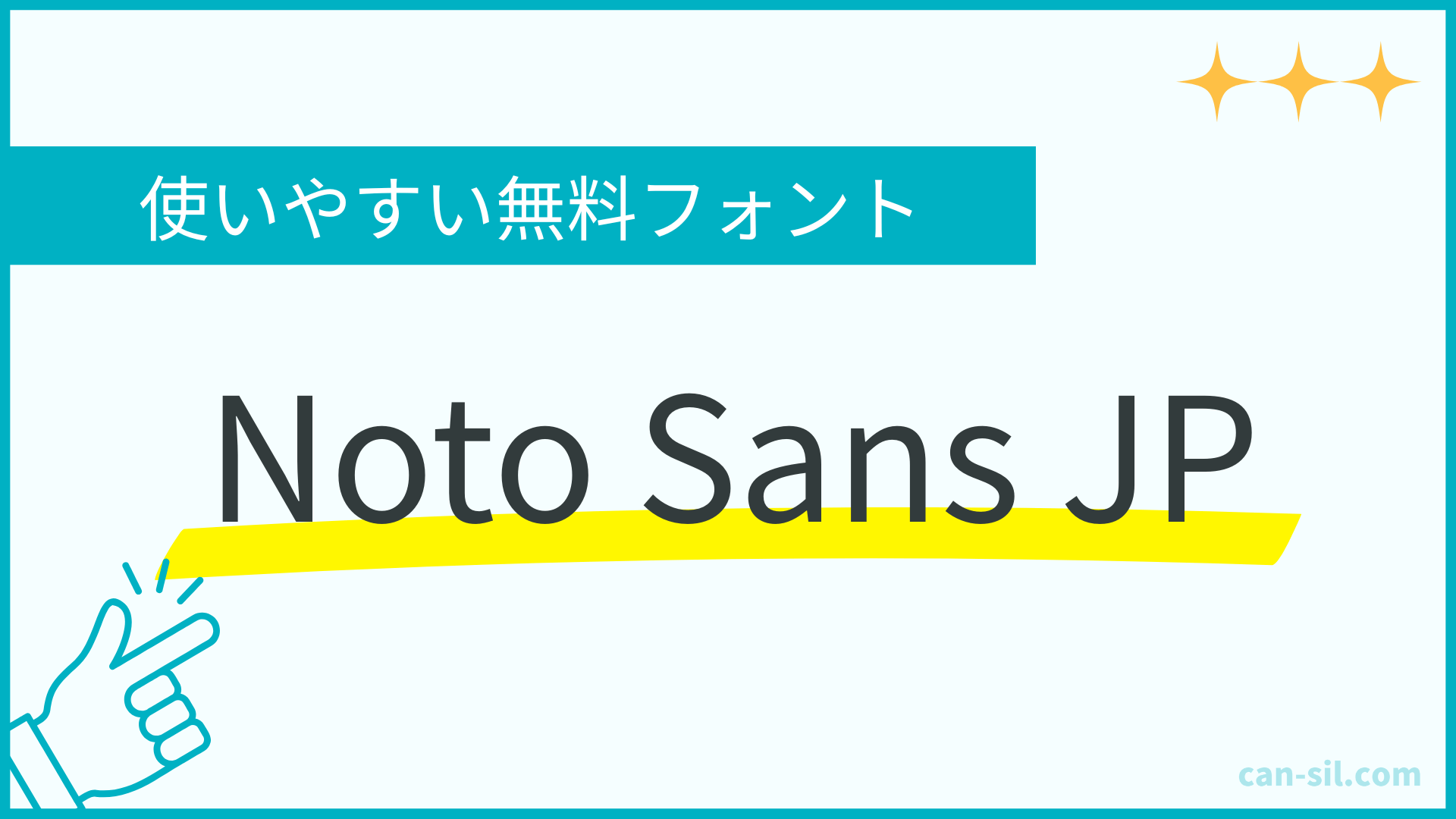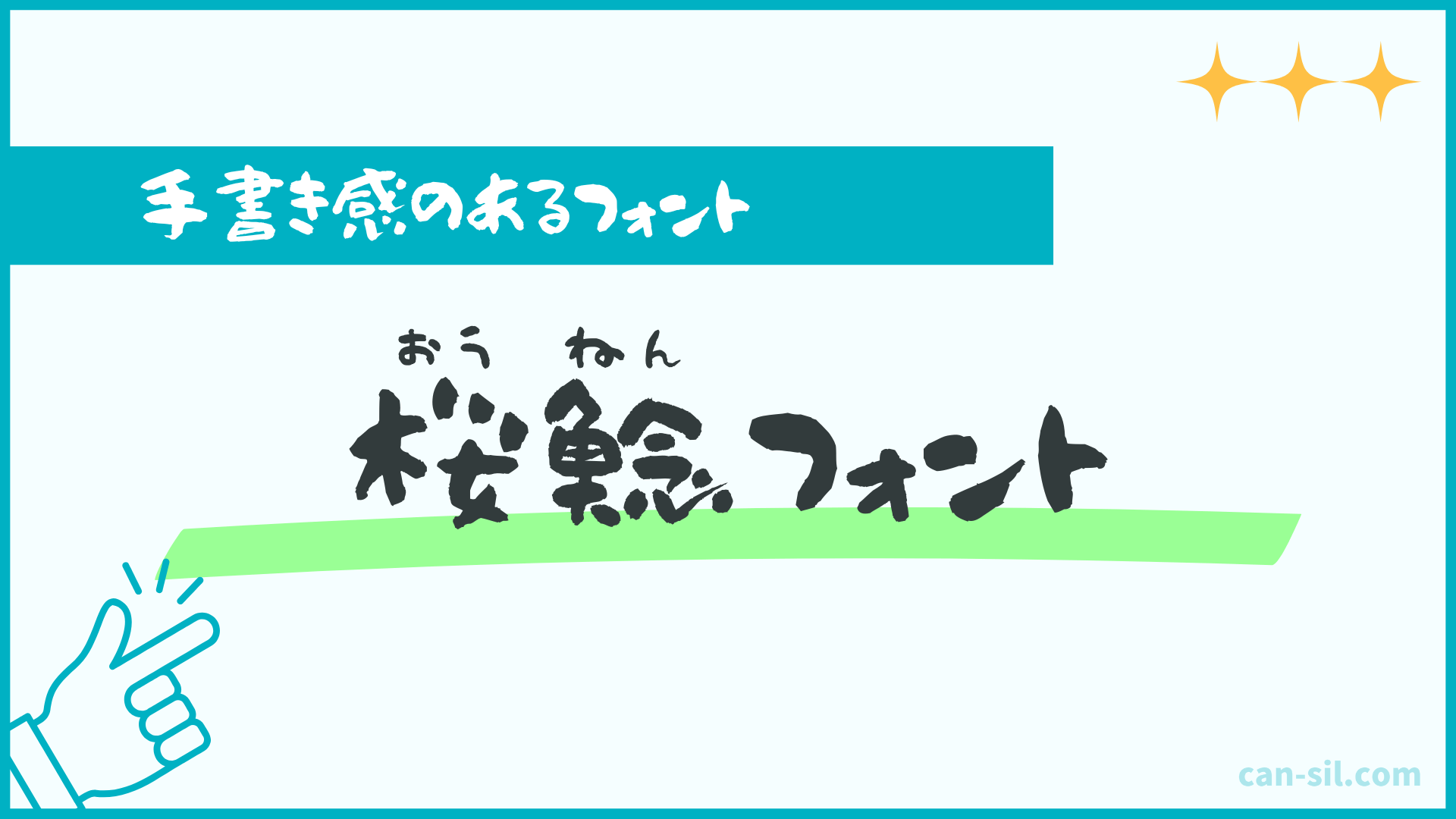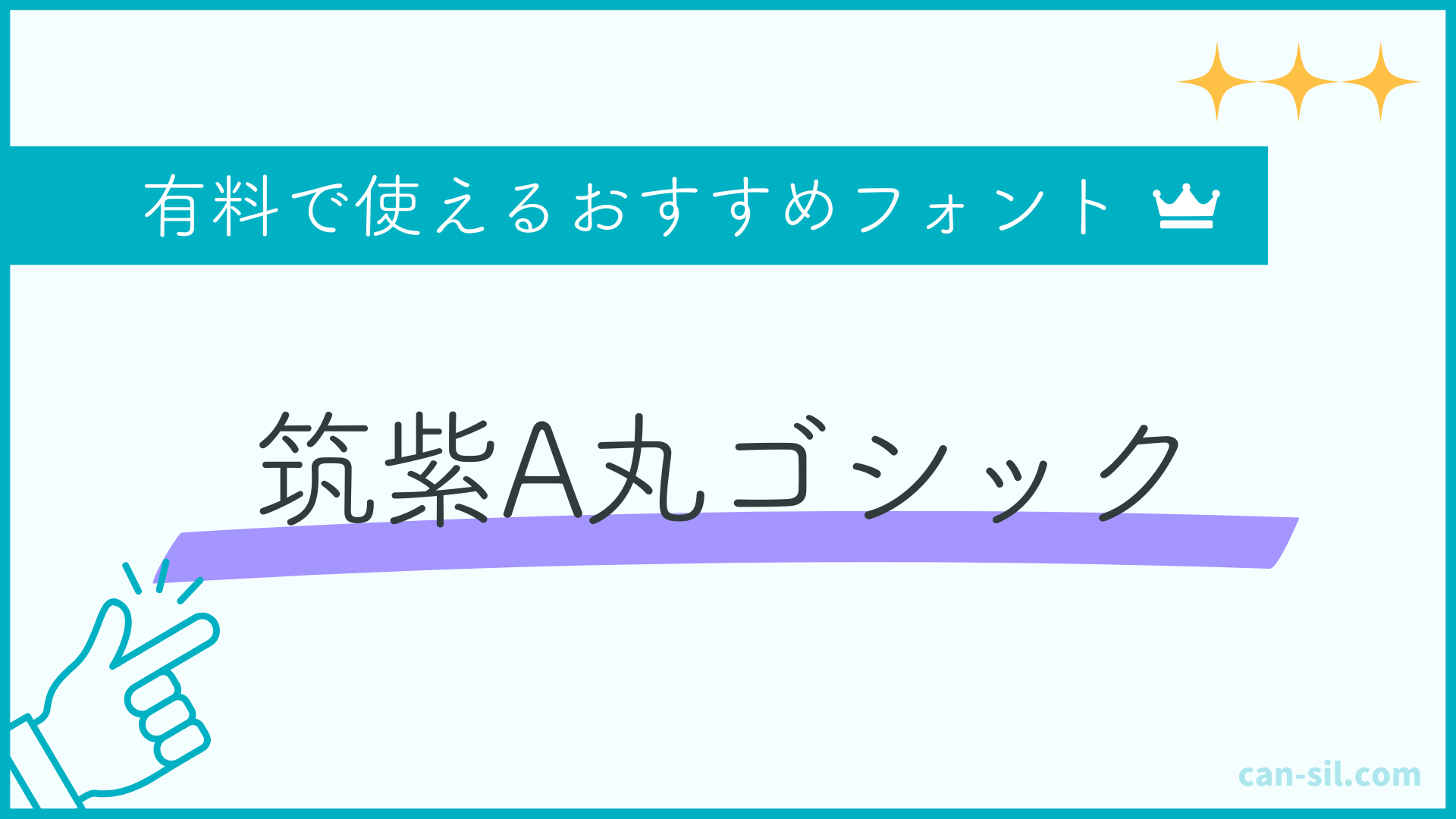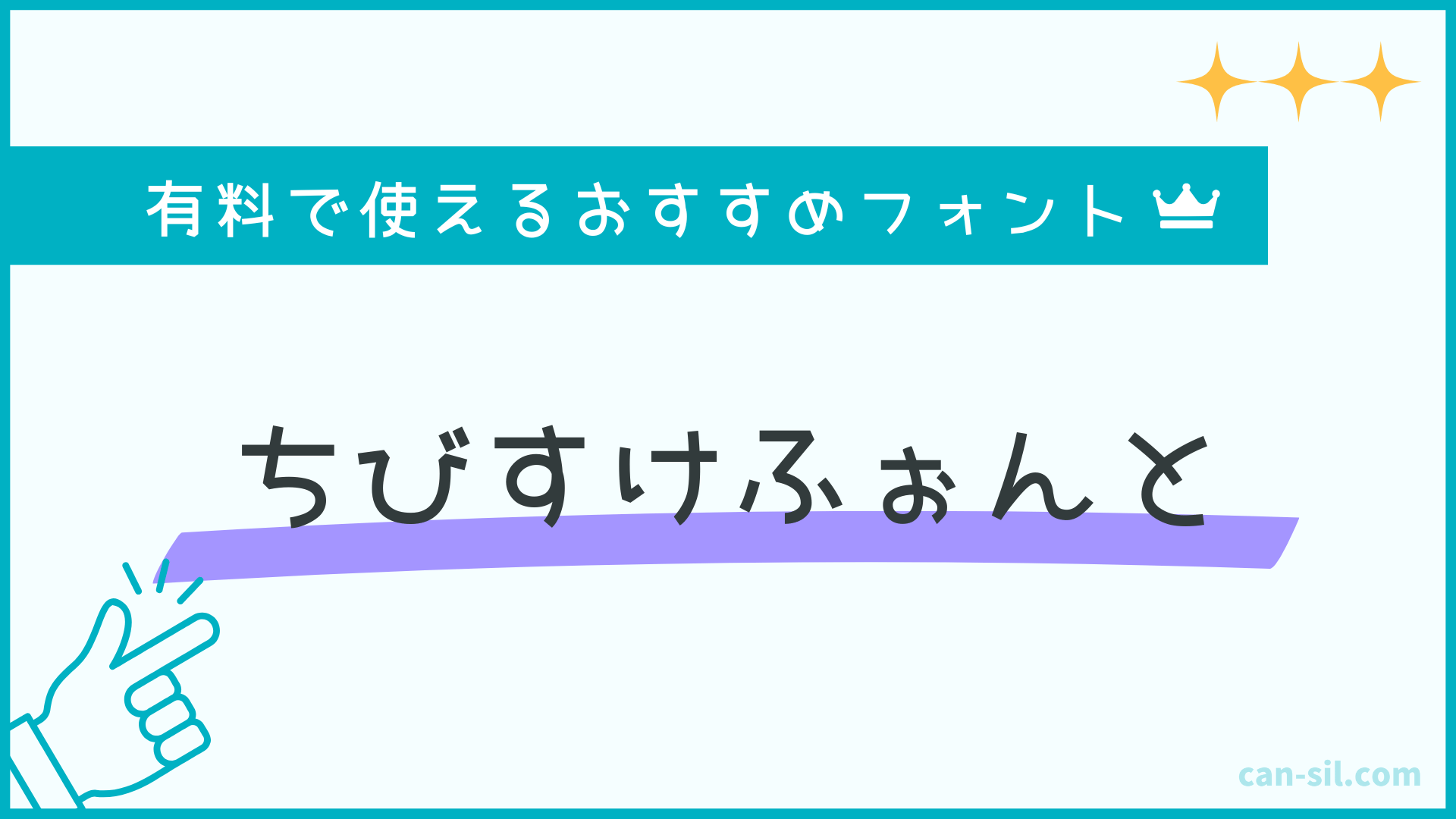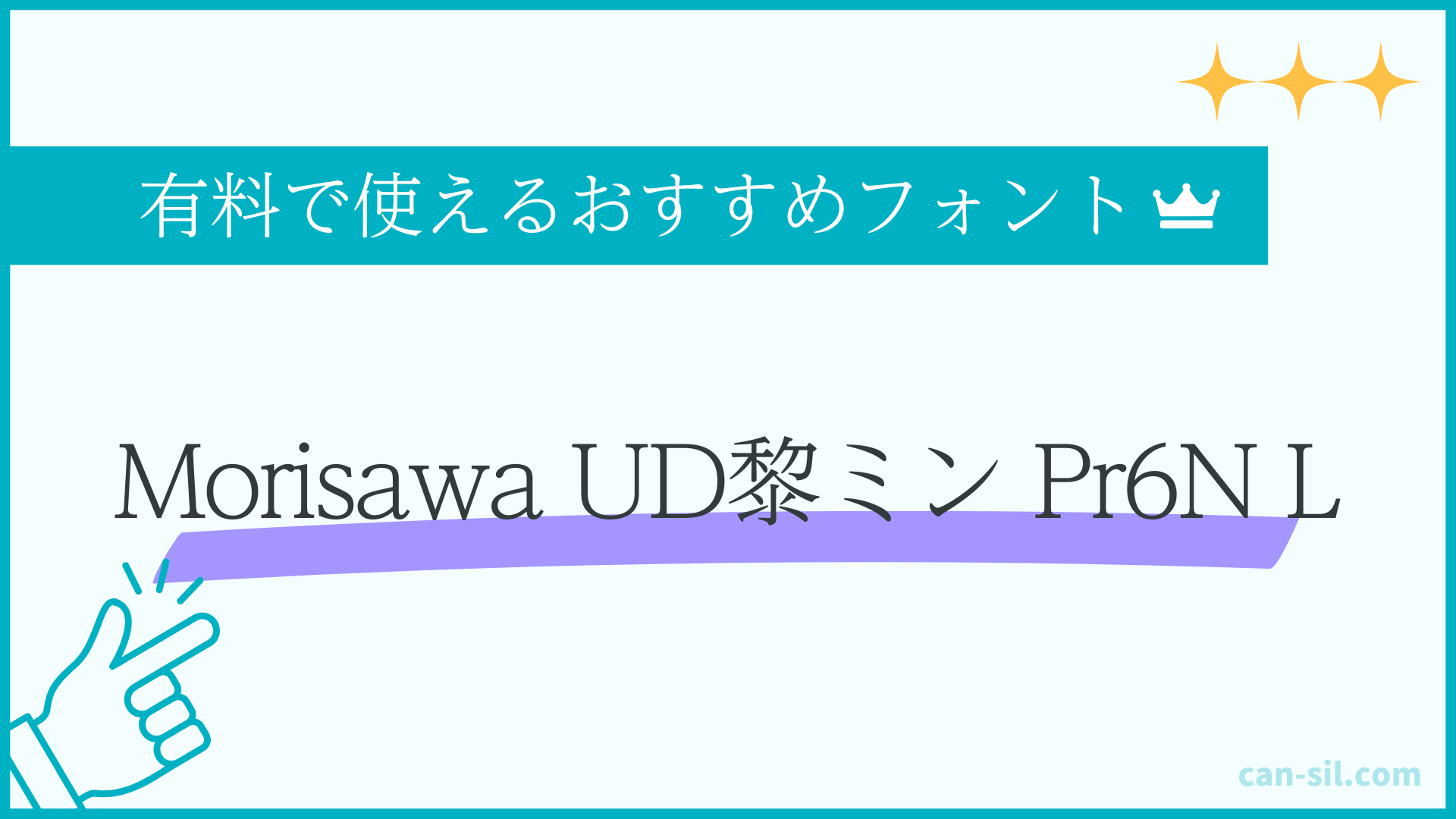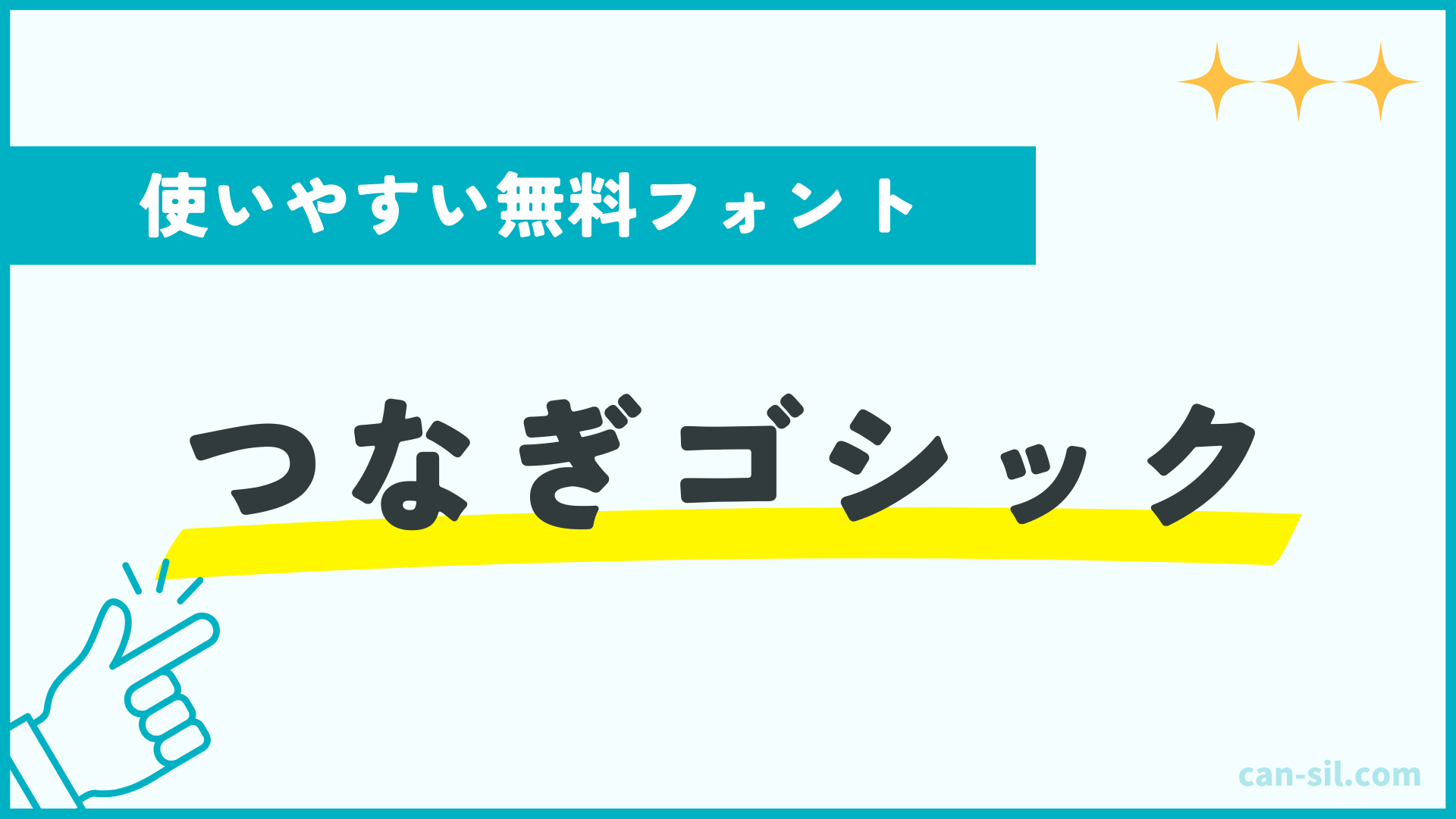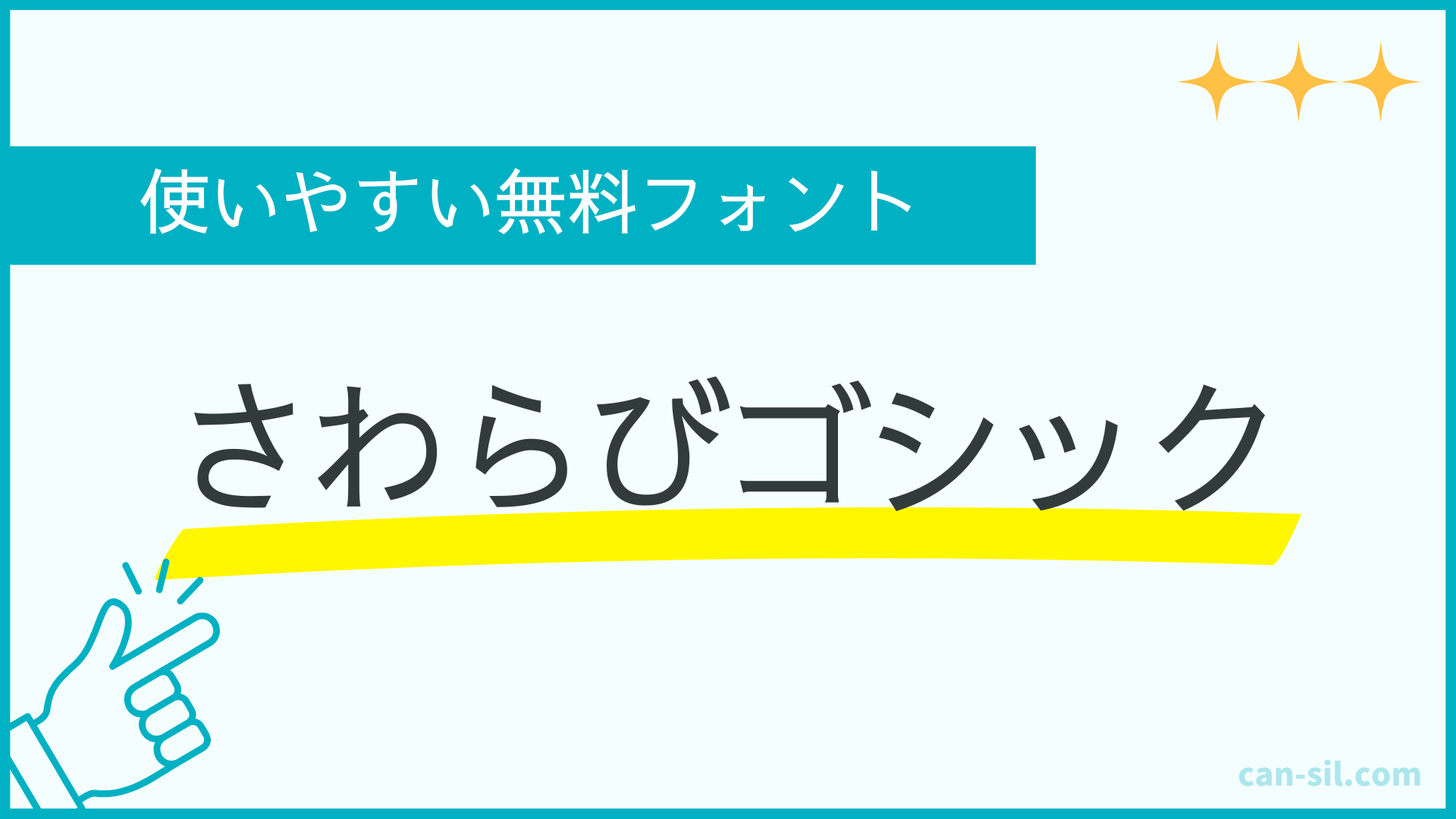
Canvaのおすすめフォント12選!アップロード方法や便利機能などもあわせて解説
Canvaフォントおすすめ12選とアップロード方法と便利機能
• 使いやすいおすすめのフォントはどれ?
• Canvaのフォントを使いこなすコツを教えてほしい!
Canvaでフォントを決めるとき、「もっと簡単に選びたい。」「使いたいこなしたい。」と考えていませんか?
この記事では、Canvaエキスパートのぼくがおすすめするフォントをいくつか紹介します!
おすすめフォント12選
おすすめフォント一覧
また、Canvaのフォントアップロードの方法や、より使いこなしたい人におすすめの便利機能についても、詳しく解説します。
ぜひ参考にして、明日からCanvaをもっと使いこなして、理想のデザインを実現しましょう。
Canvaでおすすめの日本語フォント12選を紹介!
Canvaおすすめフォント12選
無料で使いやすいフォント
まず最初に、無料で使える&どんなデザインにも使いやすいフォントを4つ紹介します。
ゴシック体と明朝体の2種類を紹介します。
Noto Sans JP
使いやすい無料フォント1「Noto Sans JP」
ゴシック体の中でもシンプルで使いやすいフォントです。
GoogleとAdobeにより共同開発されたフォントで、多くの言語に対応しているのが特徴です。
多くのデザインに使われている定番フォントです!
太さは6種類(極細、細め、標準、中太、太字、極太)から選べます。
つなぎゴシック
使いやすい無料フォント2「つなぎゴシック」
「Zen角ゴシックN」というフォントの角の丸を加工し、墨だまり処理をしたフォントです。太文字で文字同士がつながって見える、かわいい形のフォントです。
太さの調整はできません。
さわらびゴシック
使いやすい無料フォント3「さわらびゴシック」
可読性に優れた、線が細いフォントです。シンプルながらも手書きのような温かさも感じられます。
太さの調整はできません。
UD明朝(N仕様)
使いやすい無料フォント4「UD明朝」
UD(ユニバーサルデザイン)をコンセプトとして、高齢者や弱視の方でも読みやすいように開発されたフォントです。
太さは4種類(細め、中太、やや太め、太字)から選べます。
雰囲気が出る味わいのあるフォント
つぎに、雰囲気が出ていい感じのフォント3つを詳しく紹介します。
ちょっと印象を変えたいときに、デザインに使いやすいフォントなので、ぜひ使ってみてくださいね。
しねきゃぷしょん
雰囲気が出る味わいあるフォント1「しねきゃぷしょん」
映画の字幕を参考に作られた、映画でもよく見られるようなフォントです。
柔らかくて、スッキリしていて読みやすいのデザインになります。
字体の太さは変更できません。
にくまる
雰囲気が出る味わいあるフォント2「にくまる」
ゆるくて柔らかい雰囲気のまるまるとしたフォントで、かわいらしさを演出できます。
ゴツゴツ感がありますが、文字の内側は丸くなっています。
子供向けのデザインやホップ感を演出したいときにおすすめです。
太さ変更はできませんので、注意してください。
やんちゃポップ
雰囲気が出る味わいあるフォント3「やんちゃポップ」
かわいいポップな太めの字体の有料フォントです。元気で遊び心が豊富な作りになっています。
太さ変更はできないフォントです。
手書き感のあるフォント
Canvaには手書きで書かれたような、温かみのあるフォントがいくつもあります。
ここではおすすめの手書きフォントを3つ紹介します。
ふい字
手書き感のあるフォント3「ふい字」
手書き感のある定番のフォントで、ノートに書いたような自然な文字が魅力です。
筆圧の強弱が少ないため、柔らかくて温かみを感じられます。
太さの変更はできないフォントです。
はなぞめ
手書き感のあるフォント2「はなぞめ」
やわらかくかわいい手書き風のフォントで、やや丸みのある線が細めのフォントです。
やさしい印象で、女性向けデザインに使いやすく、ふんわり感やガーリーな雰囲気を演出できます。
太さの変更はできない字体になります。
桜鯰(おうねん)フォント
手書き感のあるフォント3「桜鯰フォント」
小学生が書いたような、素朴で不器用さを感じられるフォントです。
角がやや丸く、線の太さが一定ではなく揺れを感じる字体になっており、かわいい印象を与えています。
太さの変更はできないため注意しましょう。
有料で使えるおすすめフォント
最後に、Canvaプロやチームで使える有料のフォントを3つ紹介します。
筑紫A丸ゴシック
有料で使えるおすすめフォント3「筑紫A丸ゴシック」
文字の角が丸いゴシックで、やわらかく上品な印象のフォントです。
洗礼されたデザインで柔らかい印象も持つため、ナチュラル系や雑誌風のデザインにぴったりです。
太さは6種類(細め、標準、中太、やや太め、太字、超太字)から選べます。
ちびすけふぉんと
有料で使えるおすすめフォント2「ちびすけふぉんと」
子どもが書いたような、手書き風で丸みのあるフォントです。
素朴なかわいらしさがあるので、デザインに親しみやすい雰囲気を演出したいときにおすすめです。
フォントの太さは変更できません。
Morisawa UD黎ミン Pr6N L
有料で使えるおすすめフォント3「Morisawa UD黎ミン Pr6N L」
通常の明朝体に、UD(ユニバーサルデザイン)の読みやすさを加えた上品なフォントになります。
高級感や信頼を感じさせたいときに使えます。
太さは変えることができないため、注意が必要です。
• 「アップロード済みのフォント」から選択
フォントをアップロードするときの注意点
フォントをアップロードするときの、注意点をいくつか紹介します。
とくに、以下の2点に注意しましょう。
• ライセンスの問題
• 対応しているファイル形式
配布されているフォントを使用するときは、必ずWebサイト上の規約を確認してください。
アップロードの際は、埋め込みライセンスが必要です。また、商用利用できるかは確認しておくと安心です。
使用するために一定の条件を設けているフォントもありますので、きちんと規約を読みましょう。
また、Canvaで取り込めるファイル形式かも確認が必要です。OTF、TTF、WOFFのみ対応しています。
Canvaフォントの便利機能3つ
Canvaに関する、フォントの便利機能を3つ紹介します。
便利機能をしっかり使いこなすと、より便利にCanvaのフォントを使えます。
1.無料フォントの検索ができる
2025年9月から、無料で使えるフォントが検索できるようになりました!
やり方もとても簡単です!
フォントの検索バーの右側に出てくるフィルターをクリックし、「無料」にチェックを入れましょう。
無料フォントの検索
ぺち丸
無料版を使っている人も使えるよ!
2.フォントのお気に入り登録ができる
Canvaでいつも使っているフォントを、お気に入り登録できるようになりました!
いつも使っているフォントを毎回探していた人も、安心です!
2025年9月から、フォントのお気に入り登録ができるようになりました。
下記のように、好きなフォントの右にある「⋯」をクリックすると、「お気に入りに追加」が選択可能です。
フォントお気に入り登録
「お気に入り」に表示されるフォント一覧から、使いたいフォントを探しましょう。
フォントのお気に入り登録は、50種類以上登録できました。
ただし、登録しすぎると探すのに手間がかかる場合も…。
ぺち丸
ブランドキットのフォントを登録するには、Canvaプロが必要だよ!
ブランドキットは5個まで作成できるからおすすめ!
よく使うフォントがある場合は、ブランドキットも使える!
よく使うフォントをまとめて管理したい場合は、Canvaプロのブランドキットも活用できます。
ブランドキットには、フォントやカラー、ロゴなど、デザインに必要な情報をまとめて登録できます。Canvaプロでは、ブランドキットを5個まで作成可能です。
フォントのお気に入りが増えて探しにくくなった場合は、ブランドキットも活用してみてください。
3.フォントの文字間隔を調整する
文字の間隔が広かったり、狭かったりと、文字の間隔を調整したいと感じたことはありませんか?
そんなとき、Canvaなら簡単に間隔を調整できます。
フォントの間隔を調整する手順は、下記のとおりです。
フォントの文字間隔を調整
• 「高度な設定」をクリック
• 「文字間隔」で調整
Canva内のフォントはライセンス付きで提供されています。そのため、Canva外での使用はできません。
フォントファイルをほかのアプリで使わないようにしましょう。
Canvaで提供しているフォントや素材は、基本的にCanvaを使ってデザインすれば商用利用が可能ですので、安心して使用してみてください。
Canvaのフォントを使いこなして理想のデザインを実現!
Canvaフォントを使いこなして理想のデザインに
Canvaのフォントを使いこなせるようになると、デザインの印象や伝わり方がぐっと変わります。
ぜひ紹介したフォントを使ってみて、理想の思い描いたデザインを実現してみてください。
また、Canvaに使いたいフォントがない場合は、フォントのアップロードも可能です。
フォント独自のライセンスに注意しつつ、活用しましょう。
今回紹介した情報を参考に、Canvaのフォント選びや使い勝手をよくしてみてください。